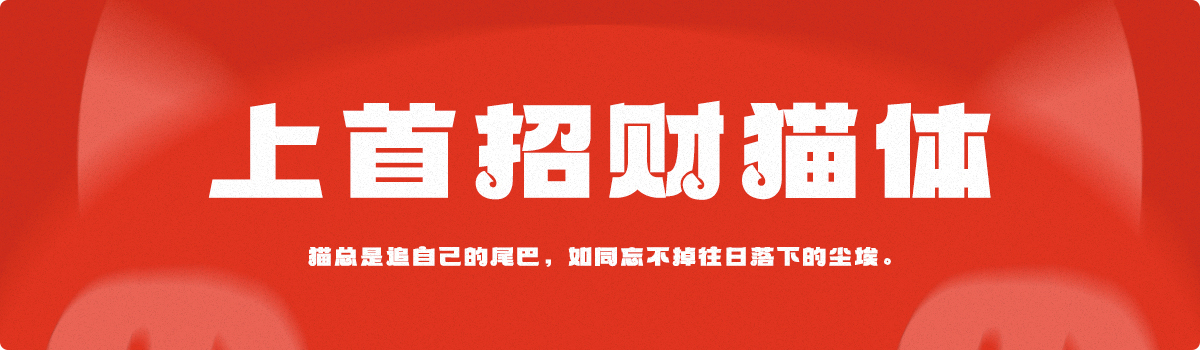
上首招财猫体
上首招财猫体,这款字体结构工整、笔画清晰,兼顾美观与易读性,适用于标题、正文、海报、包装、LOGO 等多种场景。字形优雅稳定,风格百搭耐看,适配日常排版与创意设计,让文字呈现更舒适、更具质感。上首招财猫体一笔一画,皆是细节,以均衡的比例、流畅的线条打造舒适视觉体验,字形端正大气,风格简约现代。无论是商业设计、品牌宣传还是日常排版,都能轻松驾驭,让文字更有格调与力量。上首招财猫体字体下载。